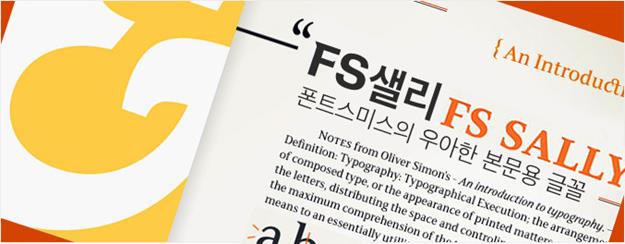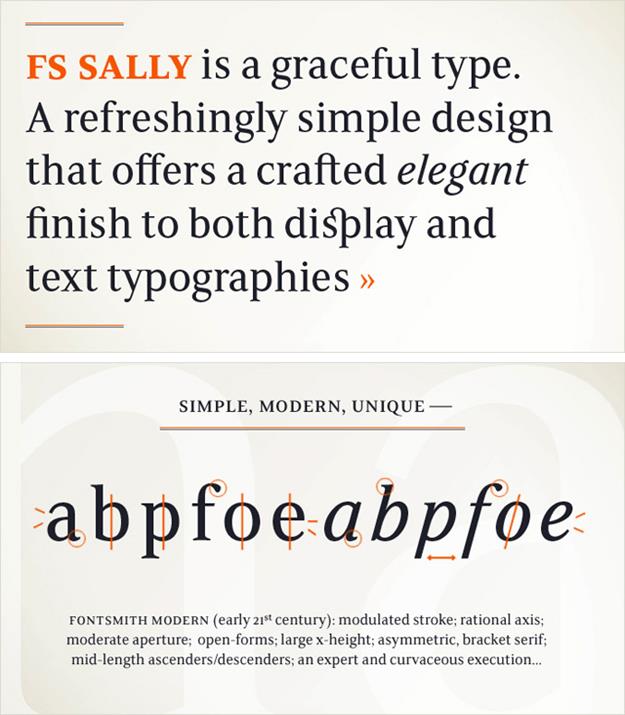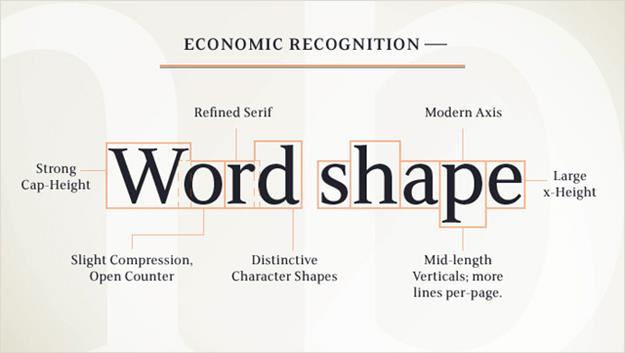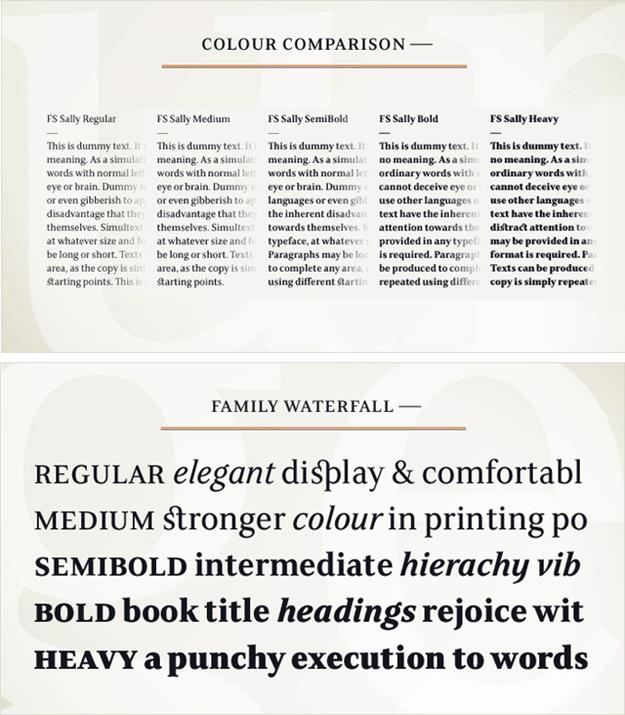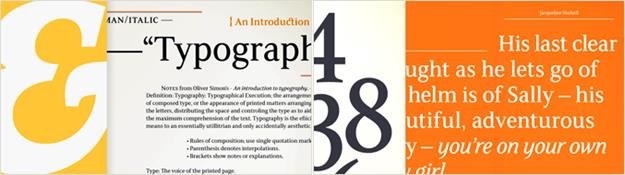
폰트스미스의 우아한 본문용 글꼴, FS 샐리
런던의 타입페이스 디자인 스튜디오 폰트스미스(Fontsmith)의 폰트 FS 샐리(Sally)를 소개한다. FS 샐리는 우아하고 품위있는 형태로 디스플레이와 본문 타이포그래피의 완성도를 높여주는 본문용 폰트이다. FS 샐리가 가진 몇 가지 특징들에 대해 자세히 살펴본다.
단순함, 모던함, 독특함
FS 샐리는 단순한 구조로 우아함이 느껴지는 폰트이다. 구조의 단순함은 본문 타이포그래피 뿐만 아니라 디스플레이에서도 완성도 높은 마감을 가능케 한다. 또한 약간의 고전적 스타일이 섞인 과도기적 모던함과 독특함은 본문의 적고 많은 양과 상관없이 침착하게 앉혀진다.
비대칭, 유동성, 리듬감
FS 샐리의 바닥부분과 숄더(shoulder)부분에서는 고전적이면서 비대칭적인 특징을 볼 수 있다. 숄더에서는 안쪽으로 휘어지고, 바닥부분에서는 바깥쪽으로 휘어지는 비대칭적 브래킷 셰리프의 설정은 활자에 리듬감을 부여한다. 특히 ‘a’, ‘d’, 그리고 ‘u’와 같은 힘있는 움직임에서 그러한 특징은 더욱 뚜렷이 나타난다. FS 샐리의 이탤릭체는 본몬용 폰트가 요구하는 일반적인 제약들은 유지하면서, 펜 글씨가 전해주는 부드러운 느낌의 움직임이 스며 나오는 것이 특징이다.
비례와 열림
FS 샐리는 적당하게 큰 X-하이트(x-height)와 보통 길이의 어센더(ascender), 디센더(descender)로 구성된다. 이 비례는 열린 활자형태와 일반적인 애퍼츄어(aperture)가 조합될 때, 보다 컴팩트하고 효율적인 활자 형태를 구현한다.
선과 컬러의 맞춤
FS 샐리의 카운터(counter)는 공간 효율성에 염두를 두고 간결하면서 열린 형태로 형성된다. 이는 고전적 서체 디자인과 조화를 이루며, 텍스트에 편안하면서 신선한 분위기를 제공한다.
소대문자
FS 샐리는 완전한 소대문자 세트를 가진다. 이 소대문자들은 다음과 같은 환경에서 기능적으로 활용된다.
– 헤드라인
– 약어와 머리글자의 설정
– 새로운 장(chapter)의 첫 글자 설정
– 본문 속 강조 텍스트
연자 활자
다른 본문 폰트들 처럼 FS 샐리 역시 표준형 연자 활자와 본문에서의 가독성보다는 FS 샐리만의 타이포그래피적 스타일을 덧붙인 단독형 연자 활자 세트를 가진다. 이 연자 활자는 사용자의 소프트웨어 디폴트(default)로 실행된다.
패밀리 웨이트와 적용
FS 샐리 패밀리는 레귤러(regular), 미디움(medium), 세미볼드(semi bold), 볼드(bold), 헤비(heavy)의 5가지 웨이트로 구성된다. 레귤러는 디스플레이에서는 우아하고, 확장 본문에서는 쾌적한 가독성을 가져다 준다. 미디움은 레귤러에서 미묘하게 두꺼워진 웨이트로 인쇄 환경에서 완성도를 높여준다. 세미볼드의 작은 글꼴 사이즈는 레귤러에 비해 선명한 대비를 보여주고, 큰 사이즈는 서브 타이틀이나 페이지 타이틀에 어울린다. 볼드는 타이틀에 쓰이기 적합하고, 본문에서는 미디움보다 강한 대비로써 유용하게 활용될 것이다. 마지막으로 헤비는 포스터의 타이틀이나 워드 마크(word-marks)에 이상적이다.